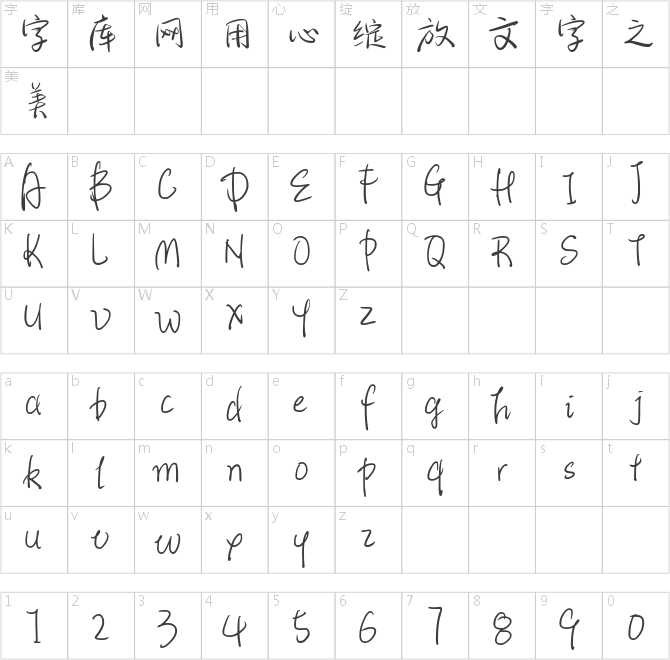
OZ焦糖下午茶 詳情頁
字體名稱: OZ焦糖下午茶
OZ焦糖下午茶
OZ焦糖下午茶字體下載OzCaramel焦糖體
OZ焦糖下午茶字體OzCaramel焦糖體字庫是一款讓人賞心悅目、百看不厭的中文字體,適合各類廣告和產品包裝設計應用,字體大小14.89MB,格式為ttf字體,上傳用戶是金蟬設計,作者/版權方為新蒂/王維